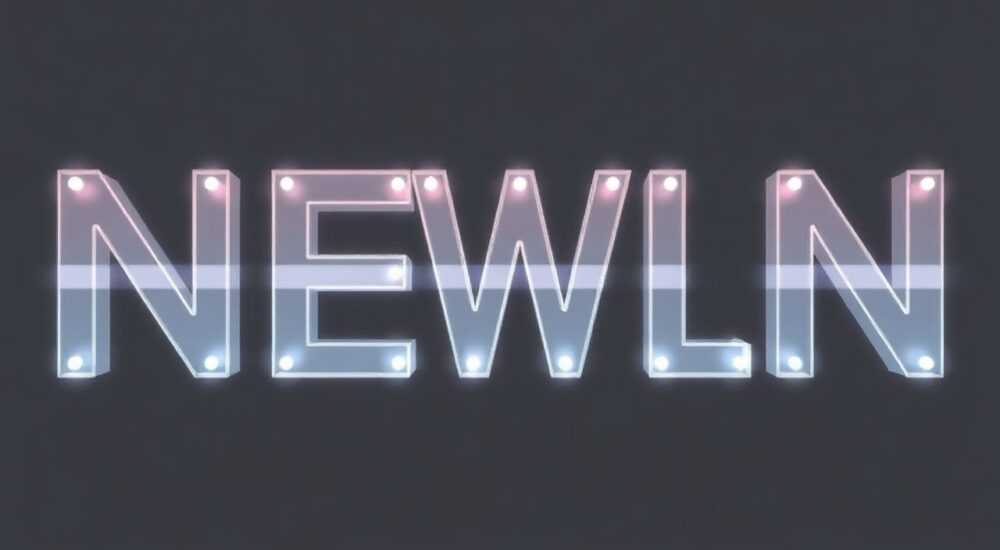
Как сделать прозрачный шрифт в фотошопе
Прозрачный шрифт в Photoshop — это эффект, при котором текстовая заливка становится прозрачной, но остаётся видимой только по контуру или сквозь фоновое изображение. Добиться такого результата можно несколькими способами: через настройки стиля слоя, маски, каналы или режимы наложения. Наиболее универсальный и быстрый метод — использование параметра «Заливка» (Fill) в панели слоёв.
Зачем нужен прозрачный шрифт и где он применяется
Прозрачный шрифт — это не просто модный тренд, а мощный инструмент визуальной коммуникации. Он позволяет акцентировать внимание на форме текста, не перегружая композицию. Такой эффект часто используется в брендинге, рекламных баннерах, социальных сетях и обложках музыкальных треков.
Представьте логотип на фоне городского пейзажа: буквы будто вырезаны из изображения, и сквозь них просвечивает закат. Это создаёт глубину, динамику и запоминающийся визуал. Прозрачность текста особенно эффективна, когда нужно подчеркнуть концепцию «пустоты», «невидимости» или «технологичности».
В дизайне одежды такой приём применяют для принтов, где текст должен гармонировать с тканью, а не доминировать. В цифровых интерфейсах — для полупрозрачных подсказок и водяных знаков. Главное преимущество — сочетание читаемости и эстетики.
Метод 1: Прозрачность через параметр «Заливка» (Fill = 0%)
Это самый простой и популярный способ создания прозрачного текста. Он не требует сложных манипуляций и идеально подходит для новичков.
- Откройте Photoshop и создайте новый документ или откройте существующий проект.
- Выберите инструмент Текст (T) и добавьте надпись на холст.
- Убедитесь, что активирован текстовый слой в панели «Слои».
- В нижней части панели найдите параметр Заливка (англ. Fill). По умолчанию он установлен на 100%.
- Перетащите ползунок до значения 0%.
Теперь содержимое текста станет полностью прозрачным, но останутся все применённые эффекты слоя — обводка, тень, наложение градиента и другие стили.
Добавление эффектов для усиления визуала
Чтобы текст не потерялся, добавьте стили слоя:
- Обводка — задаёт чёткий контур вокруг букв.
- Внутреннее свечение — создаёт мягкое свечение внутри прозрачной области.
- Наложение градиента — позволяет заполнить контур текста градиентом, который будет виден даже при нулевой заливке.
Метод 2: Использование масок и альфа-каналов
Этот подход даёт больше контроля и подходит для продвинутых задач, например, когда нужно, чтобы сквозь текст проступало другое изображение или текстура.
- Создайте текстовый слой с нужной надписью.
- Сделайте правый клик по текстовому слою и выберите “Создать рабочую область из текста”.
- Перейдите в панель Каналы и нажмите иконку «Сохранить выделение как канал». Новый альфа-канал появится в списке.
- Снимите выделение (Ctrl+D).
- Поместите нужное изображение или текстуру на слой ниже текстового.
- Выделите этот фоновый слой и добавьте к нему маску.
- В режиме маски залейте её чёрным (Ctrl+I), затем залейте белым выделение из альфа-канала: Alt+клик по каналу → залить белым (Shift+F5 → Белый).
Теперь текст «вырезан» из верхнего изображения, и сквозь него виден нижний слой.
Преимущества этого метода
Преимущество |
Описание |
|---|---|
Гибкость |
Можно использовать любые текстуры, изображения или видео в качестве «просвета». |
Не разрушает слой |
Маска не удаляет пиксели — всегда можно отредактировать. |
Подходит для анимации |
В Adobe After Effects можно анимировать маску для эффекта «раскрытия» текста. |
Метод 3: Режим наложения и клиппинг-маски
Этот способ особенно эффективен, когда нужно, чтобы текст «впитывал» в себя изображение или цвет, оставаясь при этом структурно целым.
- Добавьте текст на холст.
- Поместите изображение или текстуру выше текстового слоя.
- Установите значение Заливка текста на 0%.
- Выделите верхний слой (изображение) и нажмите Alt + клик между слоями — создастся клиппинг-маска.
- Теперь изображение будет отображаться только внутри контура текста.
Такой приём часто используют в постерной графике и digital art.
Альтернатива: через «Выполнить контурную обтравку»
Если клиппинг-маска не срабатывает, попробуйте:
- Выделите текстовый слой.
- Щёлкните правой кнопкой → «Создать рабочую область из текста».
- Перейдите к слою с изображением.
- В меню выберите «Выделение» → «Обратить», затем удалите лишнее (Del).